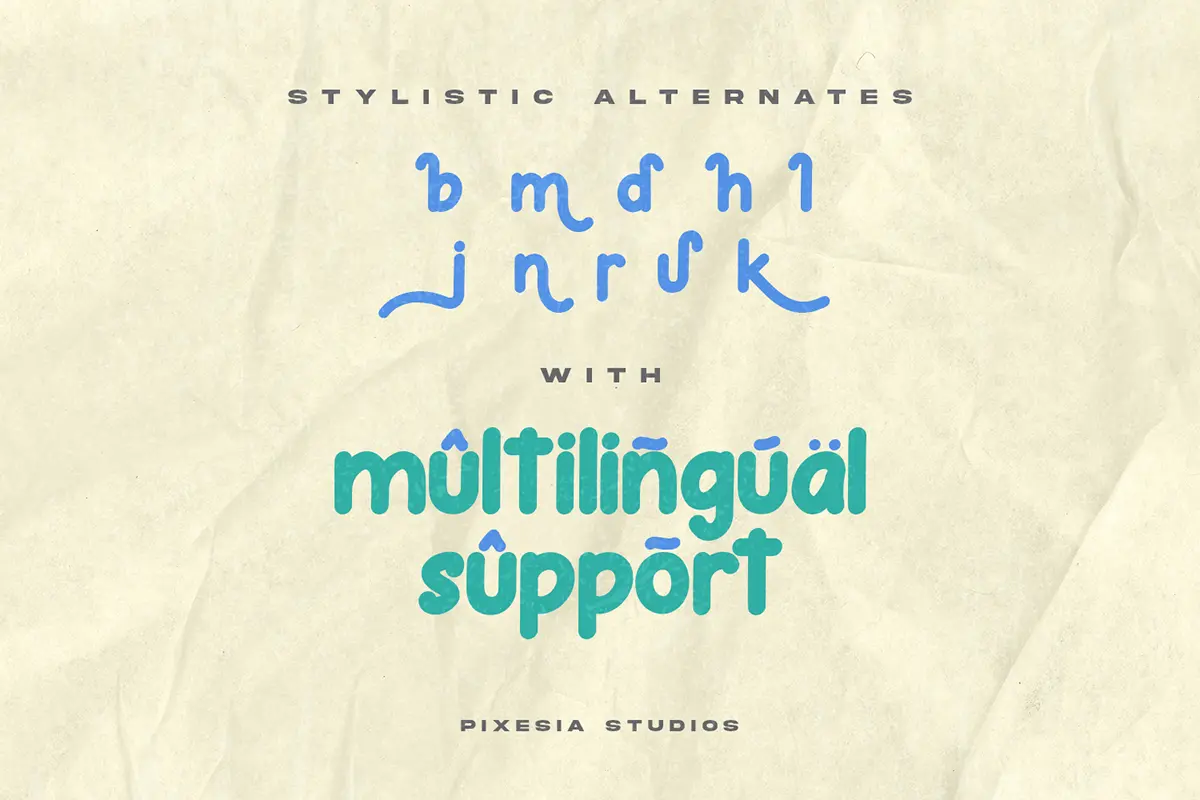
فونت نمایشی کودکانه و خوانا
فونت Dark Kids یک فونت نمایشی کودکانه و خوانا است که حس دوستانه و صمیمی را منتقل میکند. این فونت برای پروژههای خلاقانه و سرگرمکننده عالیه و میتونه بهسرعت به فونت محبوب و پرکاربردت تبدیل بشه.
⭐ ویژگیهای محصول
- فونت نمایشی با سبک کودکانه و شاد
- خوانایی بالا و مناسب برای متنهای طولانی
- انتقال حس دوستی و صمیمیت در طراحیها
🎯 موارد استفاده
- طراحی کاردستیها و پروژههای کودکانه
- ساخت کارتهای تبریک و دعوتنامهها
- استفاده در پرزنتیشنها و اسلایدهای آموزشی
- تزئین محتوای دیجیتال و شبکههای اجتماعی